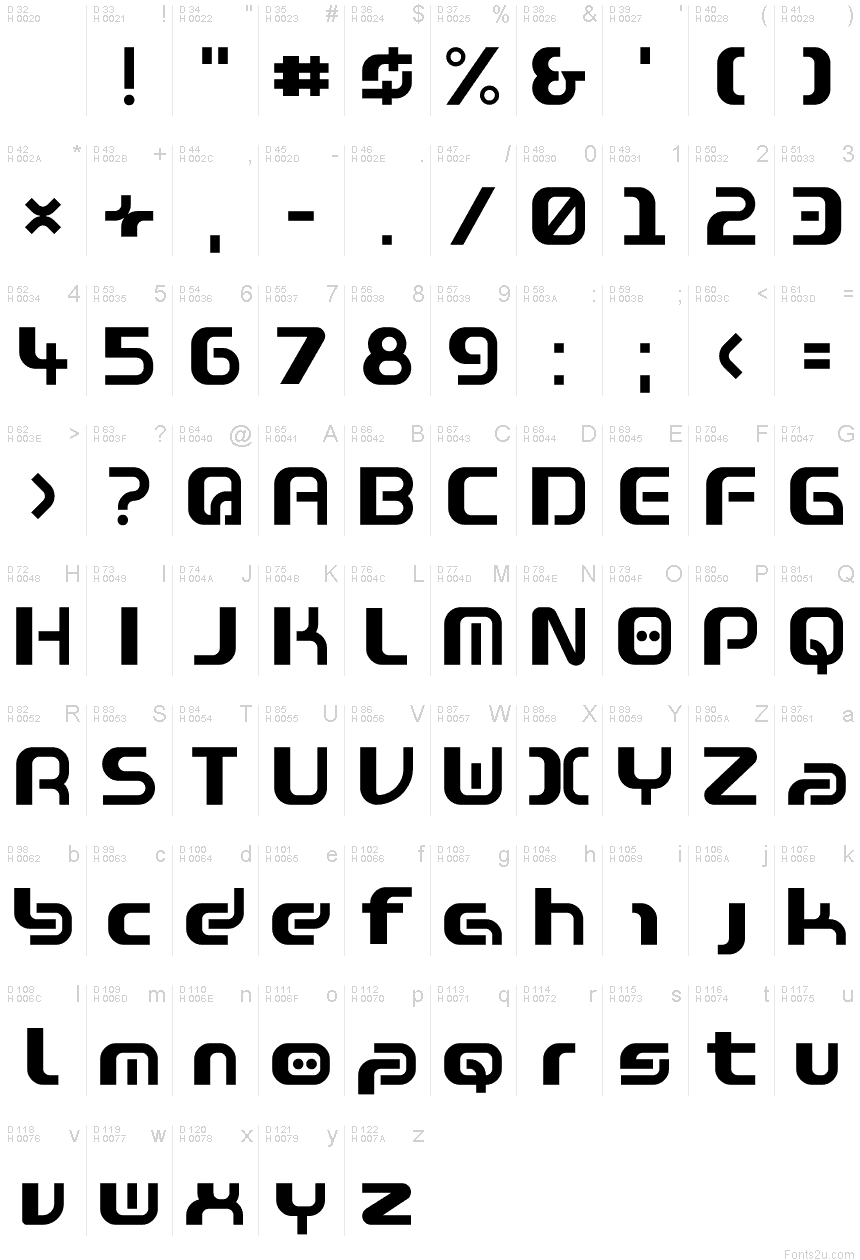
Warzone 97 Medium Left ist eine kostenlose, retro-futuristische Display-Schrift, die voll auf den Techno-Style der späten 90er Jahre setzt. Die Buchstaben sind breit, rund und präzise geformt, mit tiefen Einschnitten, glatten Ecken und einem kompakten, modularen Rhythmus – sie erinnert an Arcade-Racer oder Sci-Fi-Interfaces.
Sie eignet sich perfekt für Poster-Headlines, Game-Branding, Club-Flyer, Titelkarten und Cover-Texte, wenn ein synthetischer, zeitgenössischer Look gefragt ist. Als kostenlose Schrift funktioniert sie auch hervorragend für Logos, Monogramme und kurze Schriftzüge, da die wuchtigen Kurven und geschlossenen Formen selbst einzelnen Buchstaben eine starke, eigenständige Silhouette verleihen.
Warzone 97 Medium Left